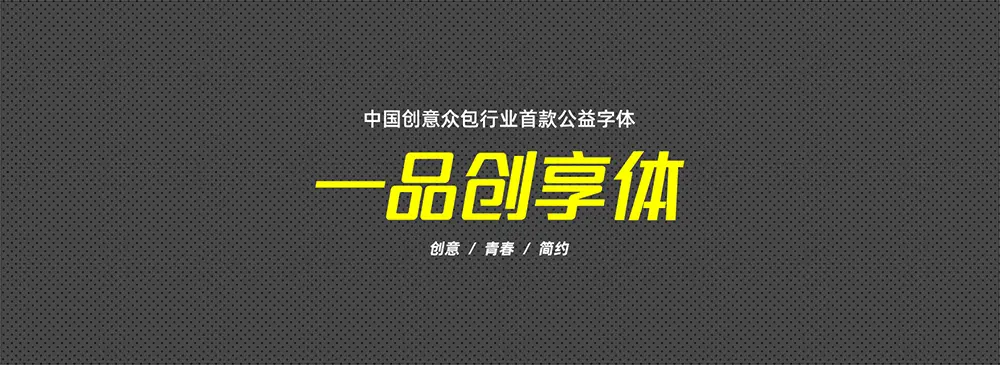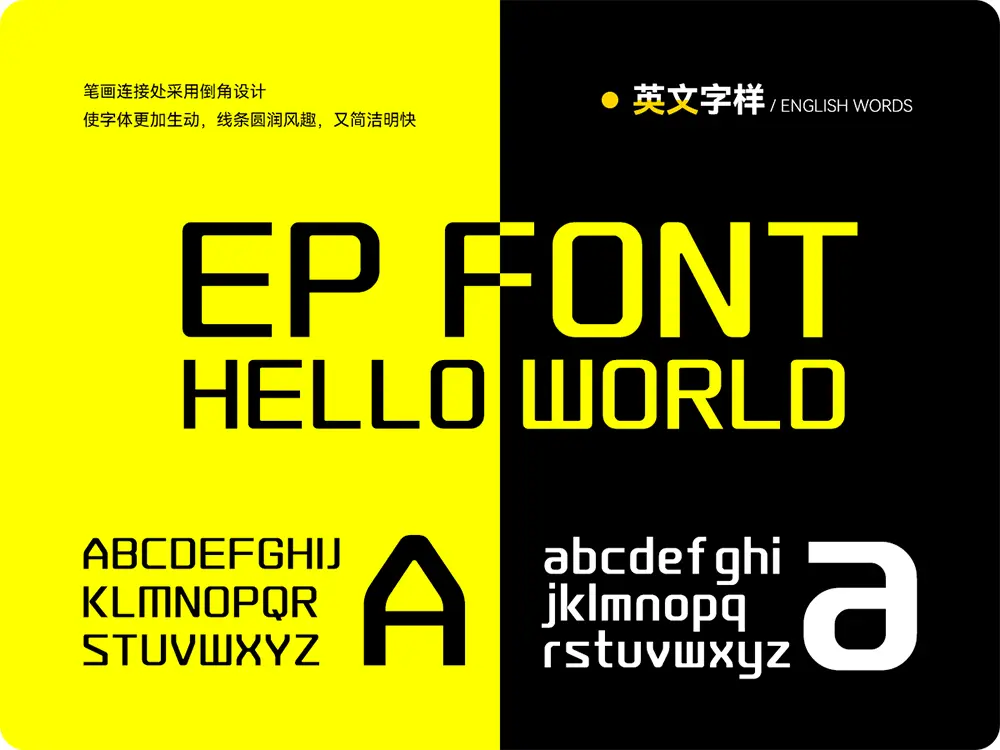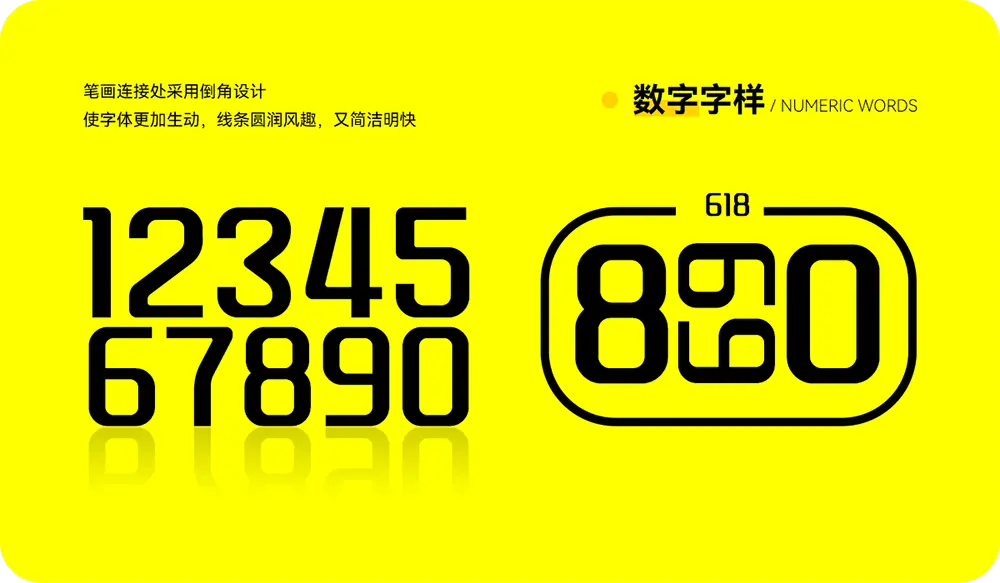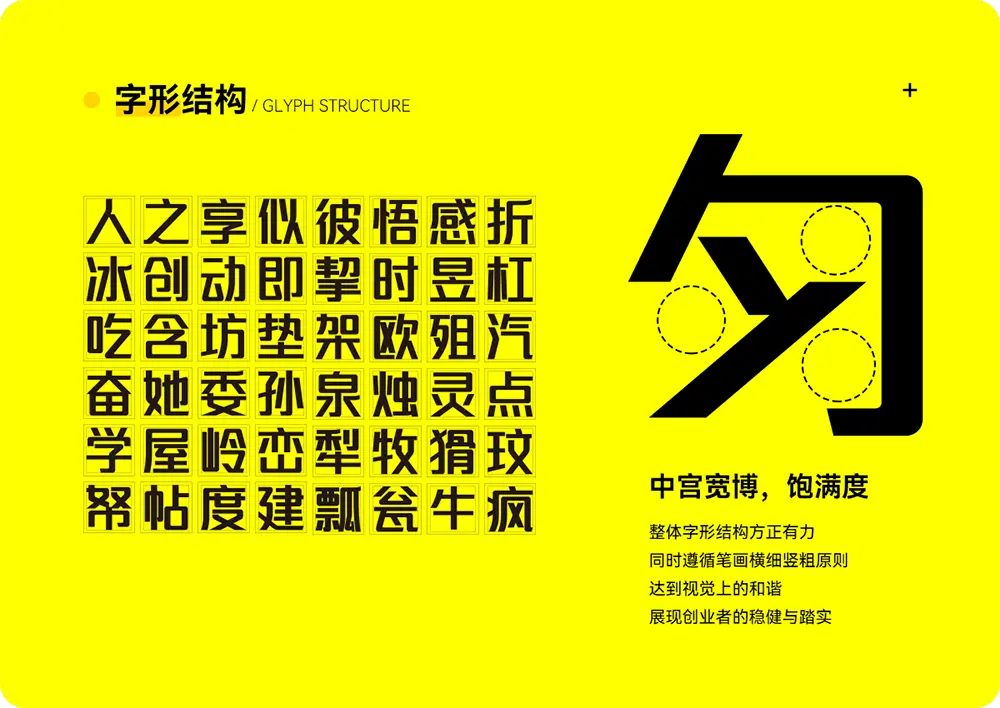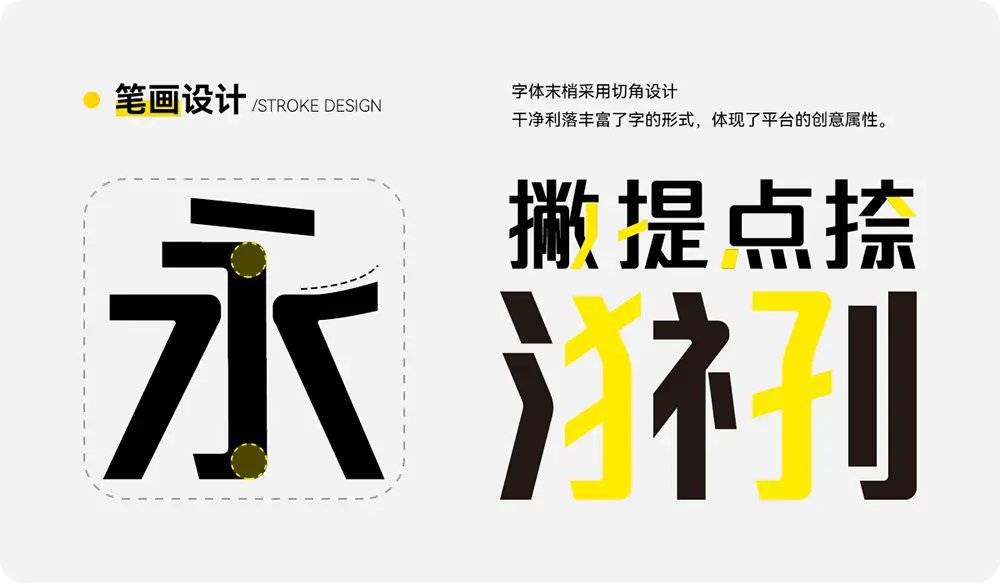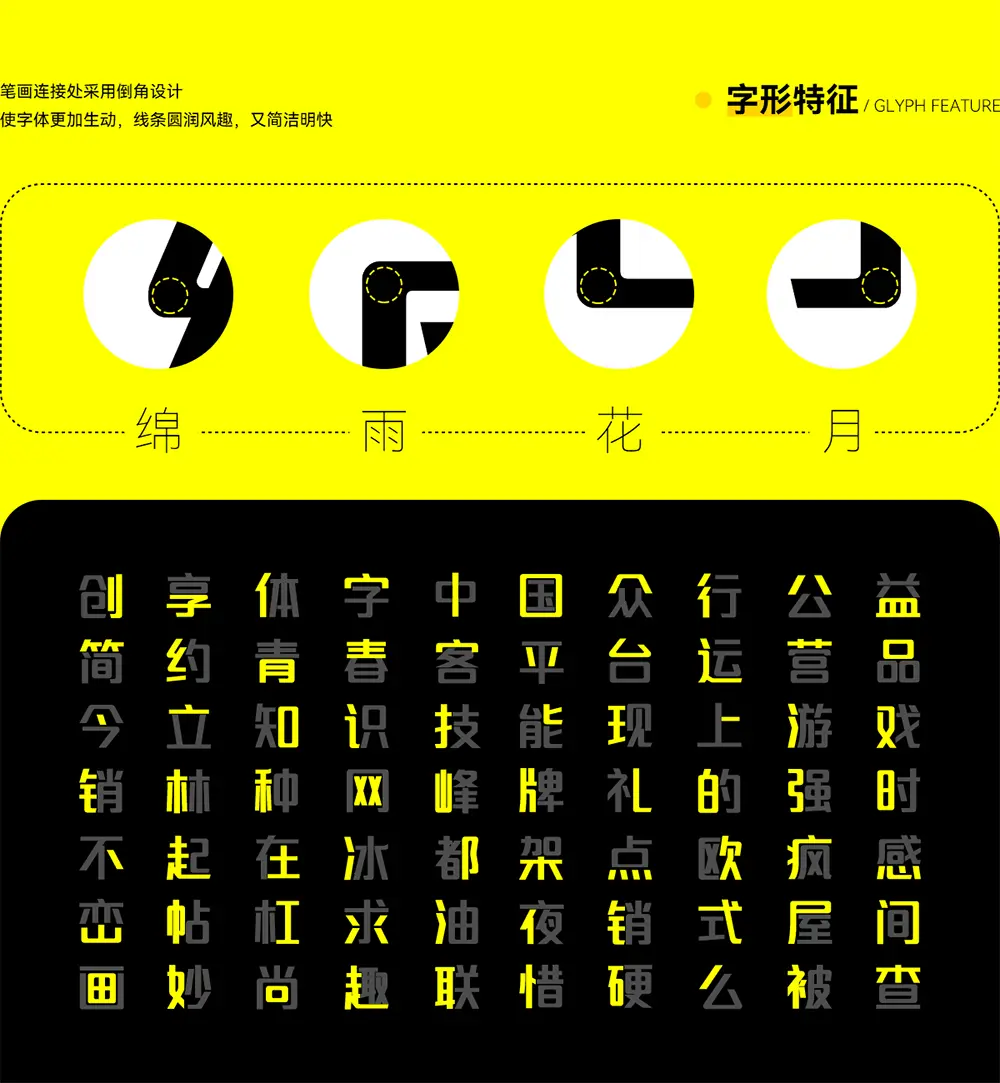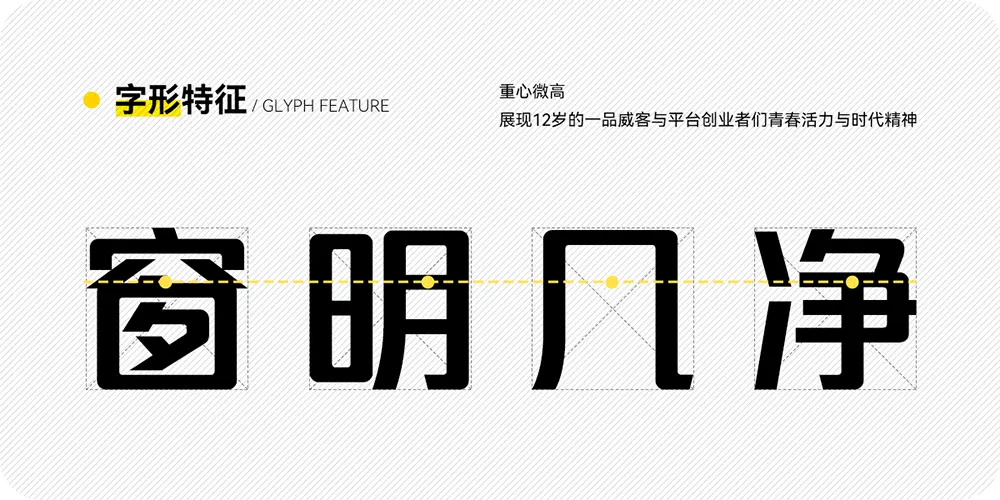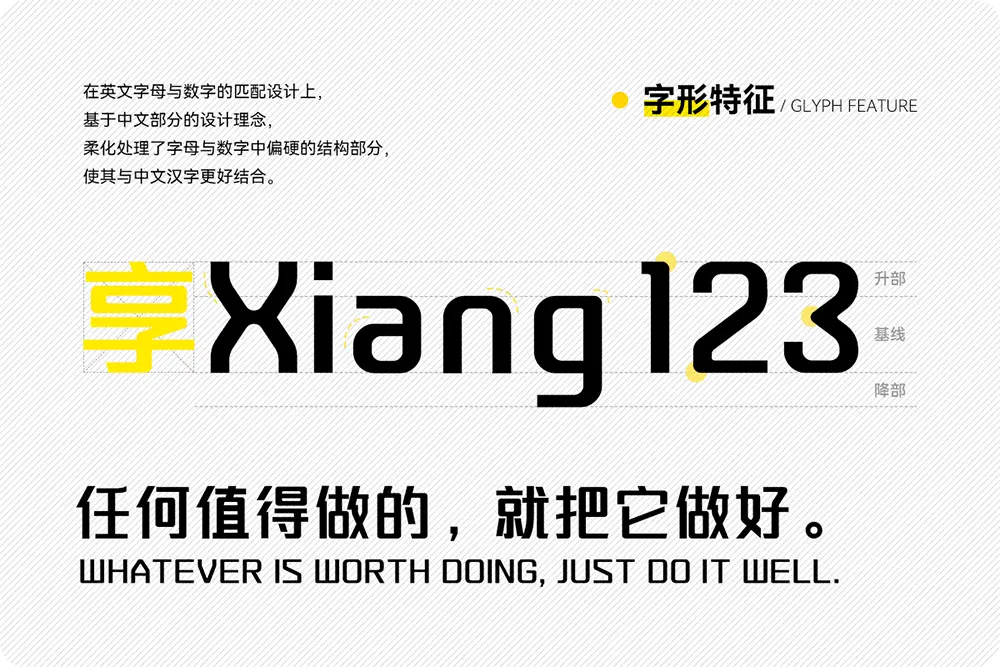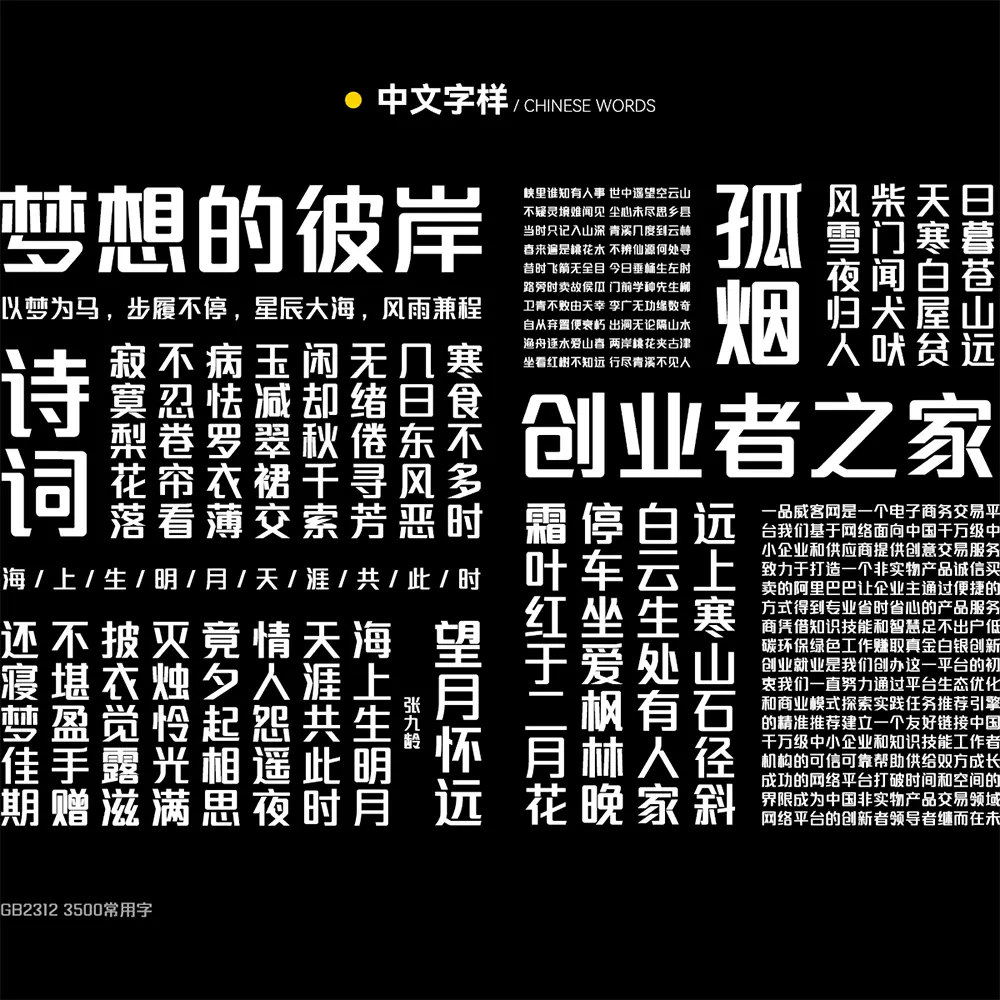
一品創享體是吉頁字庫創始人孫新恆先生受一品威客邀請作為主創設計師,聯合打造的一款公益造字百人計劃的字體,基於中華人民共和國GB2321-80字符集漢字部分標準,共收容漢字3500個,英文及標點等常用字符184個。
一人設計字庫產品要求整體風格統一、字型規範都是一件巨大而艱難的工程,此次活動由N多人參與,更是難上加難。但是,在經過小夥伴們的努力與反覆的修改,最終一品創享體還是接近完美的呈現了出來。